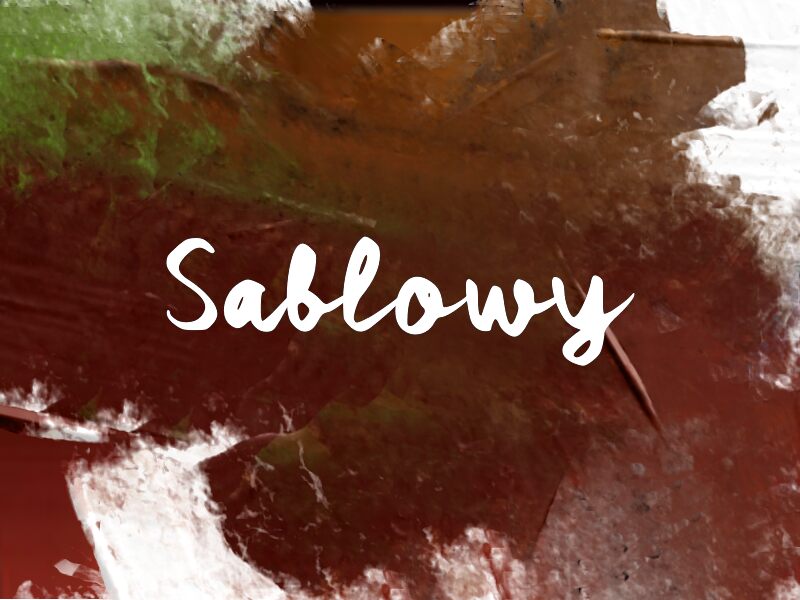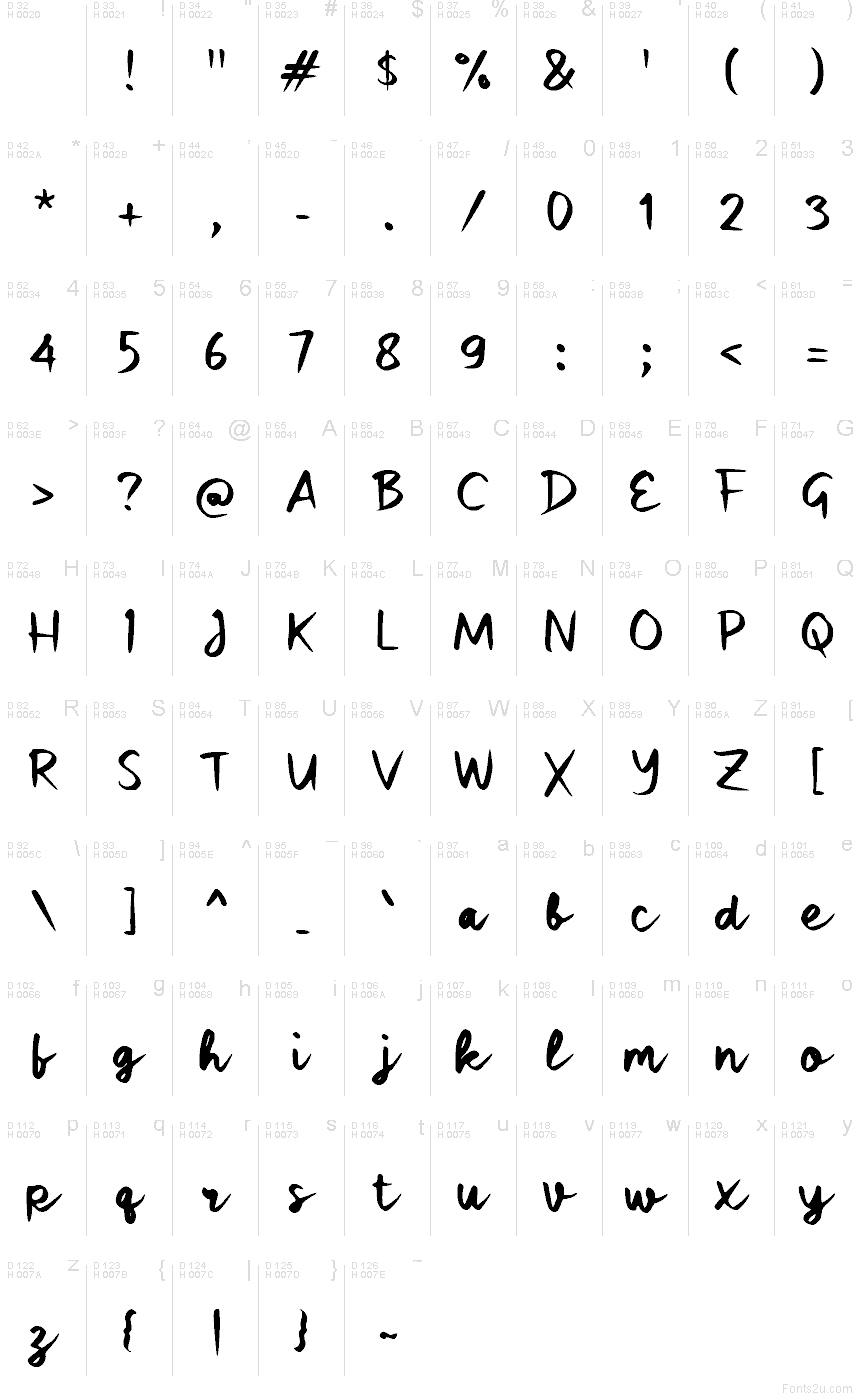
Sablowy
Sablowy, da Wep, é uma fonte manuscrita gratuita com um ritmo solto de brush-script e grandes voltas que mantêm o movimento da escrita da esquerda para a direita. Os traços arredondados e as curvas volumosas conferem-lhe um toque casual e autêntico, enquanto o final longo das letras garante um estilo vibrante, longe de qualquer restrição.
Essa energia é perfeita para branding de cafés, etiquetas de produtos, cartões, citações nas redes sociais e embalagens que pedem um toque pessoal. Títulos curtos e logotipos são os que mais beneficiam desta fonte, especialmente quando se pretende que as curvas amplas e as conexões fluidas façam todo o trabalho visual, dispensando decorações excessivas.